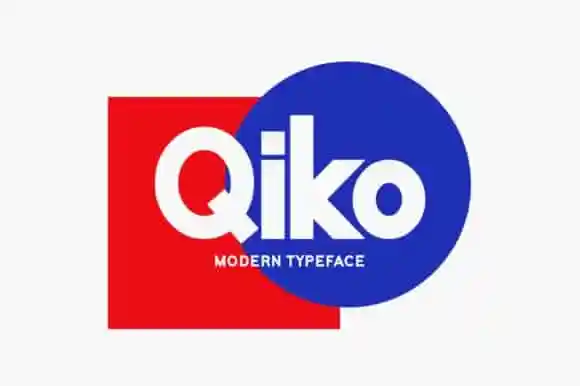
Qiko Sans Serif Font
A Qiko Sans Serif é uma nova tipografia sans serif que oferece um visual elegante e moderno. Com seu designer Seemly Fonts, essa font se destaca por sua simplicidade e casualidade. Suas letras são organizadas de maneira atraente, garantindo um olhar notável tanto em designs formais quanto informais. Com seus detalhes limpos e agradáveis, ela é perfeita para projetos variados como identificação visual (UI), logomarcas, revistas, posters e mais. A Qiko Sans Serif traz uma combinação única de elegância e modernidade à sua paleta de fontes, tornando-a ideal não apenas para uso em projetos digitais, mas também no design gráfico tradicional. Ao escolher a Qiko Sans Serif para seu próximo projeto, você terá a oportunidade de criar designs que destacam-se pela simplicidade do estilo e pelo encanto moderno desta tipografia sans serif.